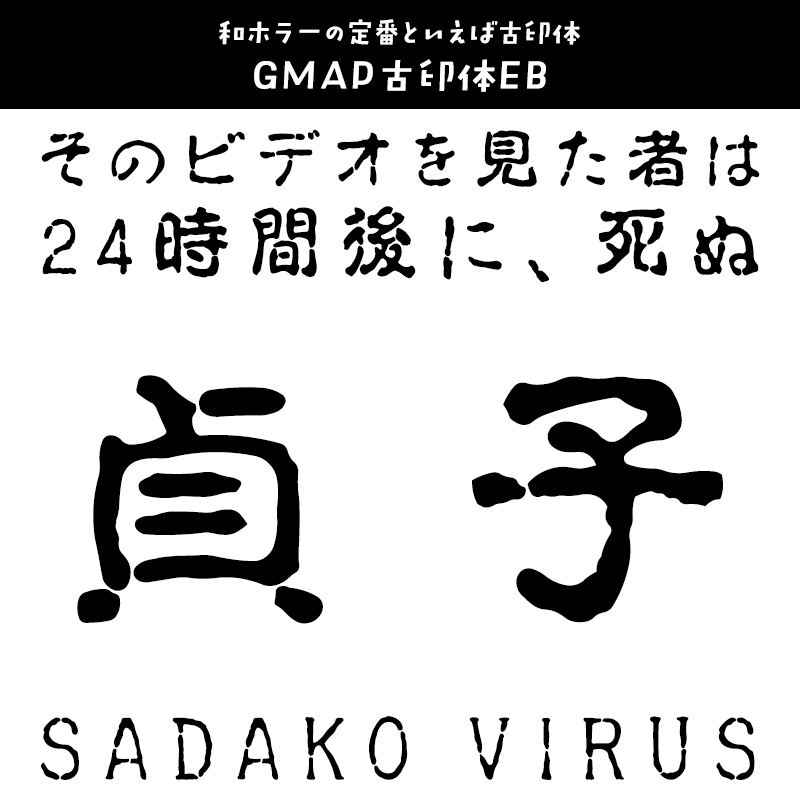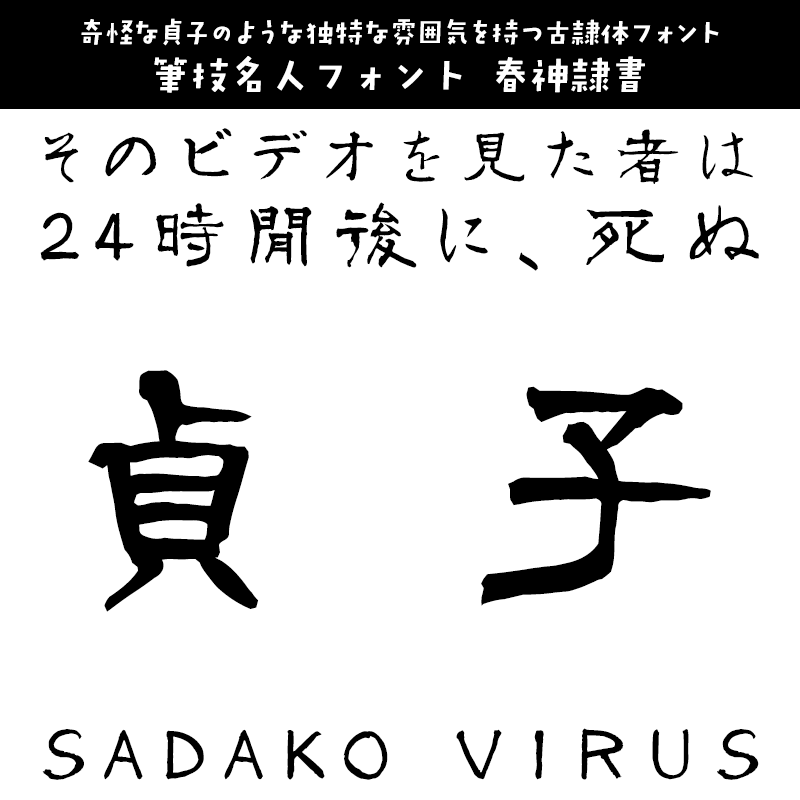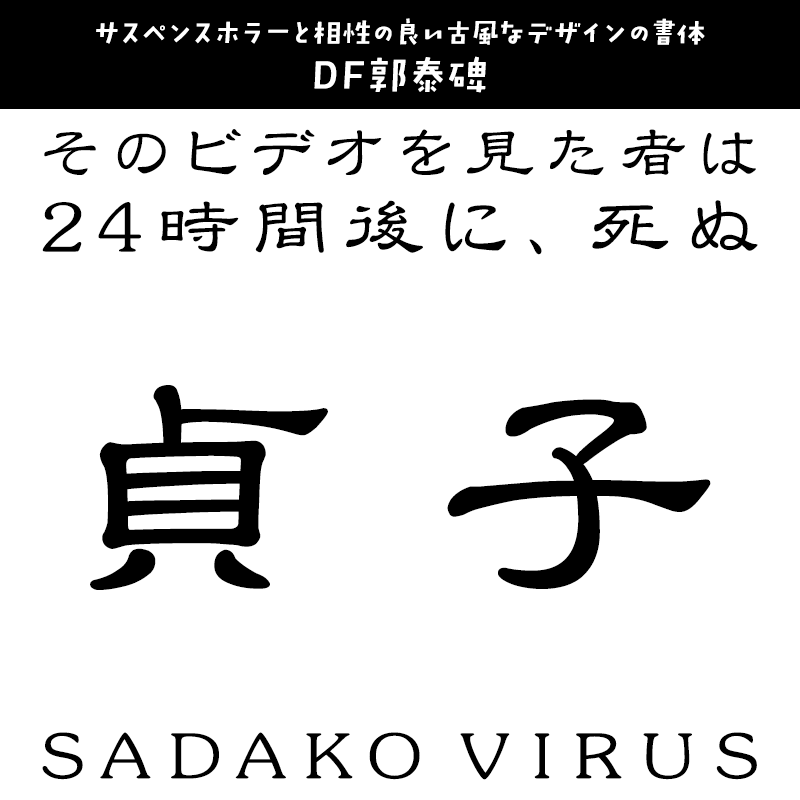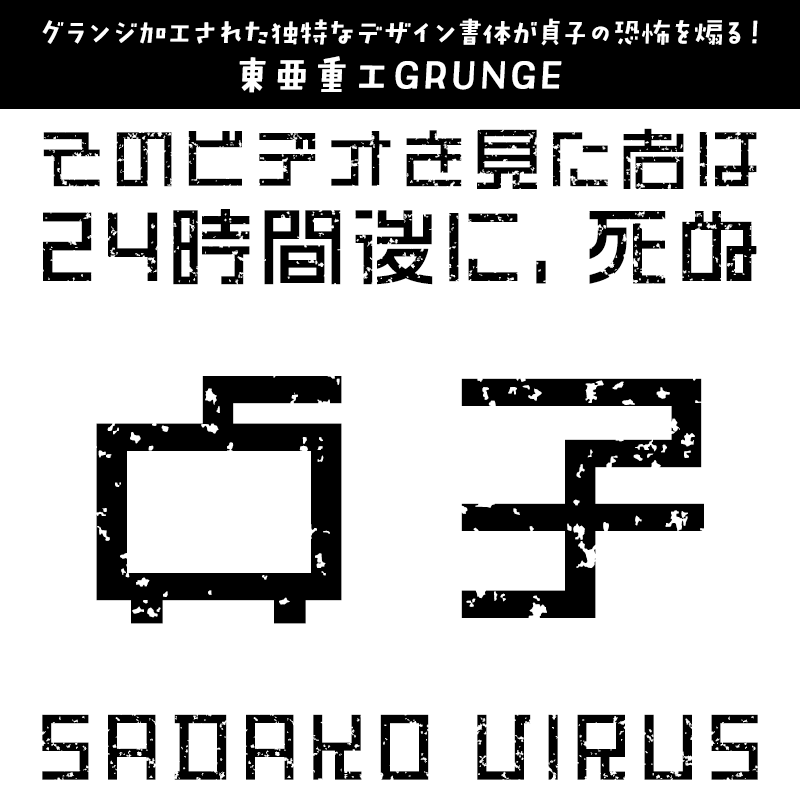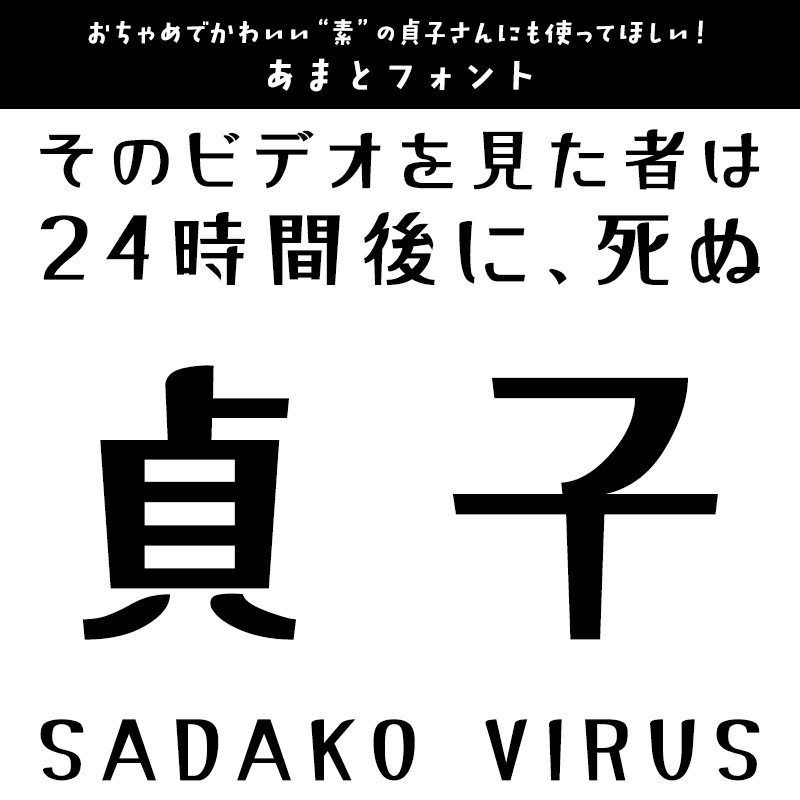
貞子に合うフォント:特化型 目的別フォントガイド #073
今回は貞子に合うフォント。日々フォントのことばかり考えている当店スタッフが直感的に選んだフォントをご紹介します。
貞子に合うフォントをスタッフが選びました
貞子に合うフォント g_コミック古印体-フルセット B 太字
ホラーのために生み出された貞子にぴったりの手書き風古印体
貞子に合うフォント g_コミック古印体-フルセット B 太字
コミックのホラーシーンのセリフに使用することを想定して作成された古印体風の手書き文字フォント。ただ怖い雰囲気なだけでなく、やや楷書に近い骨格にすることで読みやすく仕上げられています。
貞子に合うフォント GMAP古印体EB
和ホラーの定番といえば古印体
貞子に合うフォント GMAP古印体EB
隷書体に途切れを施したおどろおどろしいフォント。一定ではない線の太さが怖さを際立たせます。
貞子に合うフォント DF古印体 W5
恐怖を醸し出すホラーフォントとも呼ばれる古印体
貞子に合うフォント DF古印体 W5
石彫に書かれた文字が長い歴史の中で風化し残欠したイメージの字形、質感を表現した書体です。
貞子に合うフォント g_コミックホラー恐怖(R)
貞子の未練や恨み、そして呪いを表現するのにぴったりの古印体
貞子に合うフォント g_コミックホラー恐怖(R)
「g_コミック古印体」をベースに、コミックのホラーシーンのセリフに使用する事を想定して作成したホラーフォント。碑文っぽさもあるので歴史モノ等の積年のうらみを表現するのにも最適です。
貞子に合うフォント g_コミックホラー悪党(B)
貞子の禍々しさを表現するのにぴったりの恐ろしげなフォント
貞子に合うフォント g_コミックホラー悪党(B)
「g_コミックホラー恐怖(R)」をもとに、より禍々しく物騒で恐ろしげに存在感を強めた太字版ホラーフォント。悪人、邪悪さ、険悪さ、嘲笑感を表現できます。
貞子に合うフォント DFホラーA W5
揺れる線が恐怖を煽る!
貞子に合うフォント DFホラーA W5
わかりやすく恐怖に震える様子を表したデザインが、動画のサムネイルにも使いやすいジャパニーズホラーみ溢れる書体です。
貞子に合うフォント DF大河体 W12
ジャパニーズホラーヒロイン貞子にピッタリの毛筆フォント
貞子に合うフォント DF大河体 W12
筆文字ならではの勢いや力強さを表現した女性書道家による毛筆系書体です。起筆や払いの勢い、豪快かつ極太な筆画がジャパニーズホラーヒロイン貞子にピッタリの毛筆フォントです。
貞子に合うフォント 筆技名人フォント 春神隷書
奇怪な貞子のような独特な雰囲気を持つ古隷体フォント
貞子に合うフォント 筆技名人フォント 春神隷書
隷書体の中でもより篆書に近く、特徴的な「古隷」を選んで作った歴史を感じる隷書体フォント。ホラーシーン、恐怖演出にもピッタリの独特な雰囲気を持つフォントです。
貞子に合うフォント デザイン筆文字フォント雨点
細い筆が貞子の怪しげな雰囲気を表現する書体
貞子に合うフォント デザイン筆文字フォント雨点
手書きの温かみと細い筆が古印体風のような印象がある書体です。
貞子に合うフォント DFシネマ凜 W4
そこにあるだけで不気味さを演出する書体
貞子に合うフォント DFシネマ凜 W4
どこか古めかしさを感じさせる字幕書体は、ホラー映像に重ねるだけで不気味な雰囲気を演出します。
貞子に合うフォント DF郭泰碑
サスペンスホラーと相性の良い古風なデザインの書体
貞子に合うフォント DF郭泰碑
郭泰碑に使用されていた文字をベースに、変化に富んだ筆画の美しさで伝統的な隷書の風格を表現した書体。
貞子に合うフォント 弘道軒清朝体現代版/復刻版Pro
美しくも力強い古風な雰囲気を作り出す清朝体
貞子に合うフォント 弘道軒清朝体現代版/復刻版Pro
デジタルフォント化して現代に蘇った勝海舟も開発に携わったという明治20年代の流行書体です。できる限りもとの字形を尊重して作成した「復刻版」と、古風なイメージを残しつつJISにほぼ準拠した「現代版」した2書体セットでご用意しています。
貞子に合うフォント TA明朝GF01
アンティークな印象のデザインが貞子感のある太明朝体
貞子に合うフォント TA明朝GF01
一般的なフォルムの明朝体フォントですが、極太で鋭い表情を持っています。どこかアンティークな印象のデザインで仕上げられた仮名が醸し出す独特の雰囲気がホラー作品に最適です。
貞子に合うフォント FGP続・明治教科書明朝
明朝体をベースにした恐怖心を掻き立てられる書体
貞子に合うフォント FGP続・明治教科書明朝
明治時代、主に教科書で使われていた活字を現代流にデザインして蘇らせたフォント。特に片仮名は、明治期の教科書活字の雰囲気をより濃く再現しています。一般的な日本語書体と同様に新字体の漢字を収録した「FGP続明治教科書明朝」と旧漢字を収録した「FGP続明治教科書旧字明」。さらにそれぞれについて、エッジを荒らして和紙に印刷したようなデザインの「和紙」と、墨溜まり処理を大きくして滑らかなエッジを持たせた「蜻蛉(かげろふ)」を収録した全6書体セットです。(すべてOpenType・TrueType同梱)
貞子に合うフォント 東亜重工GRUNGE
グランジ加工された独特なデザイン書体が貞子の恐怖を煽る!
貞子に合うフォント 東亜重工GRUNGE
「東亜重工GRUNGE」は、東亜重工製フォント『東亜重工』にグランジ(汚れ)加工を施したフォントです。デザインソフトなしでもステッカーなどの印刷物や画像にアクセントをつけることが出来ますので、動画やインスタなどのアイキャッチに使うとインパクト大!映画「シドニアの騎士 あいつむぐほし」の公開を記念して発売されたデザイン書体です。
貞子に合うフォント あまとフォント
おちゃめでかわいい“素”の貞子さんにも使ってほしい!
貞子に合うフォント あまとフォント
「貞子の井戸暮らし」で見せる素の表情(?)にぴったりの元気でかわいい雰囲気のフォントもおすすめです!